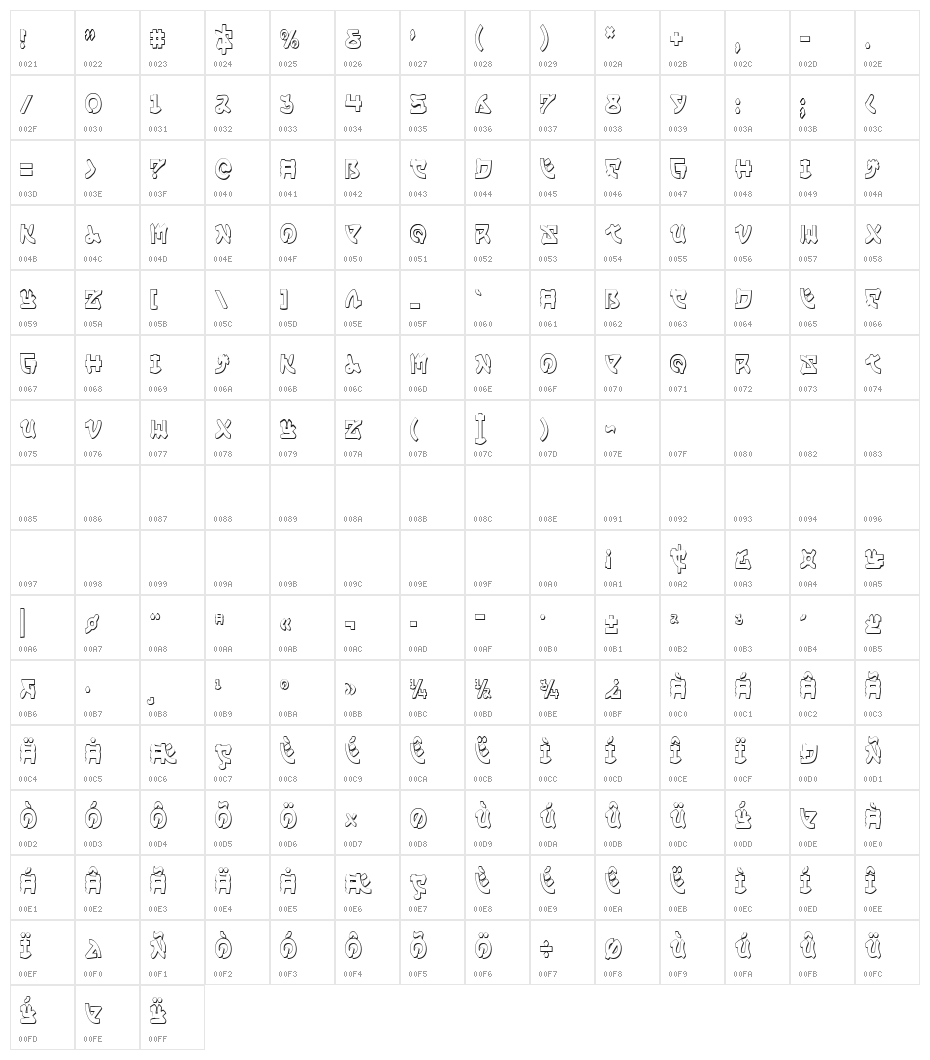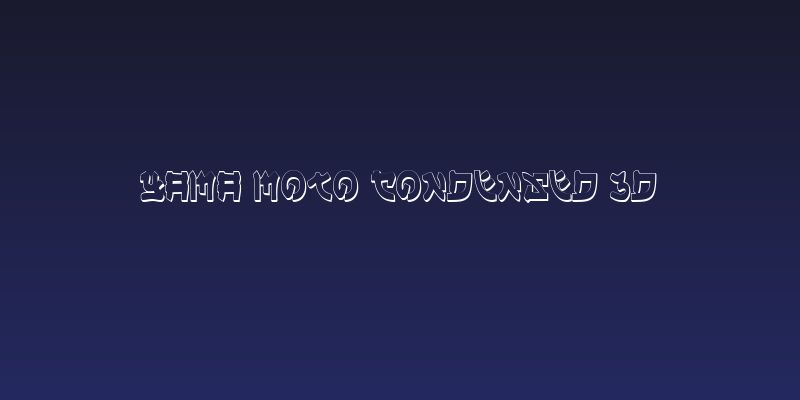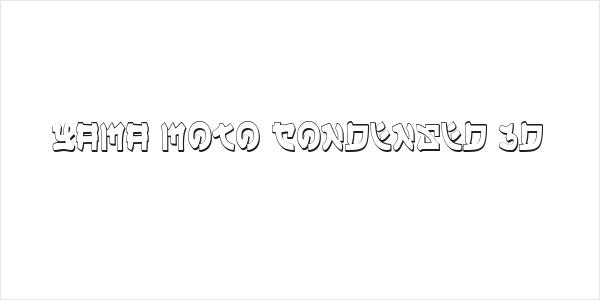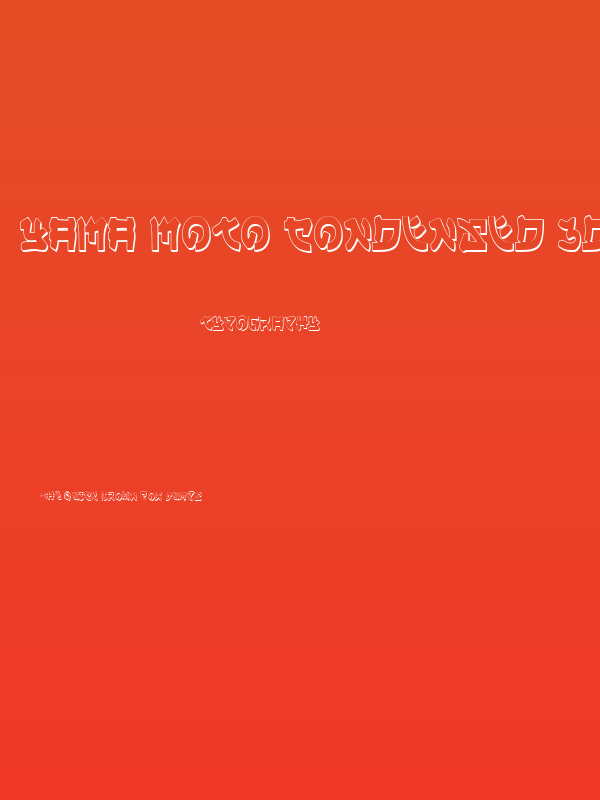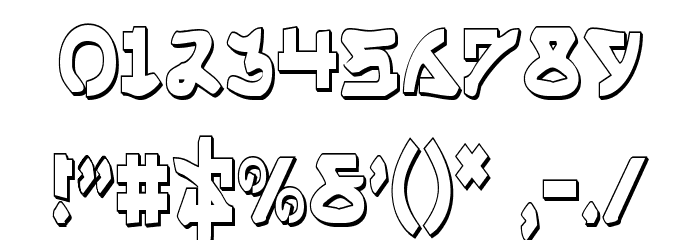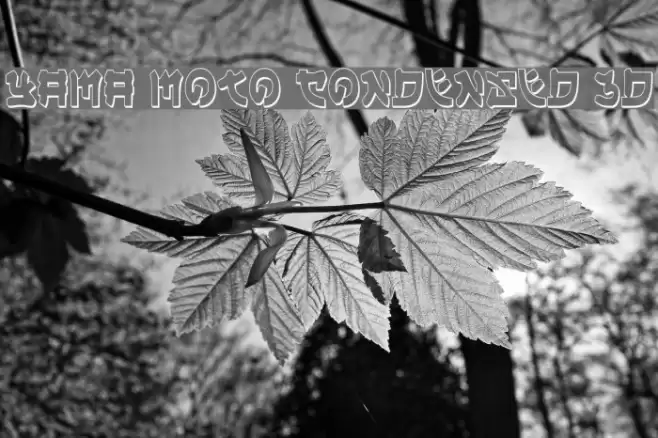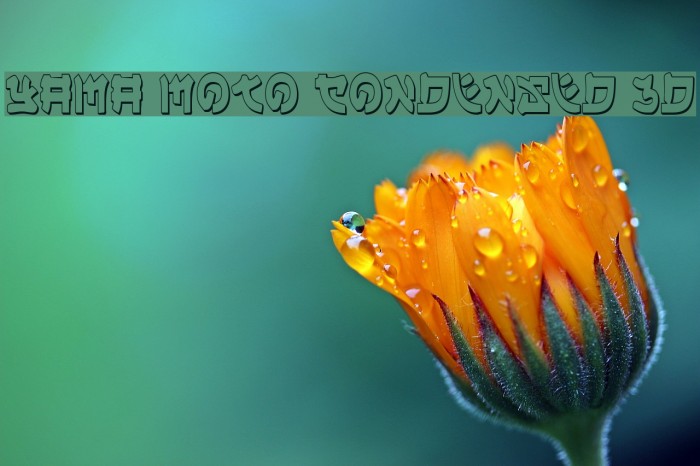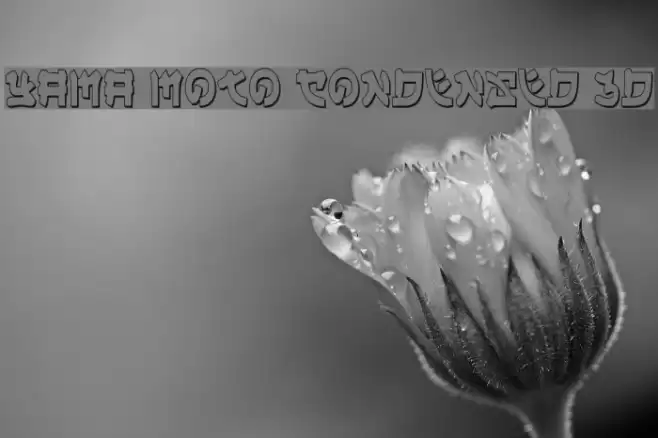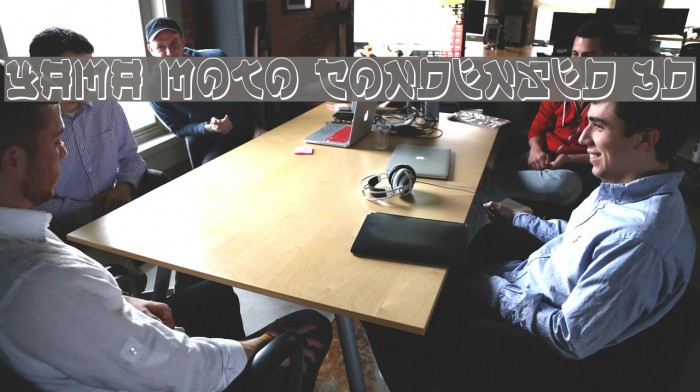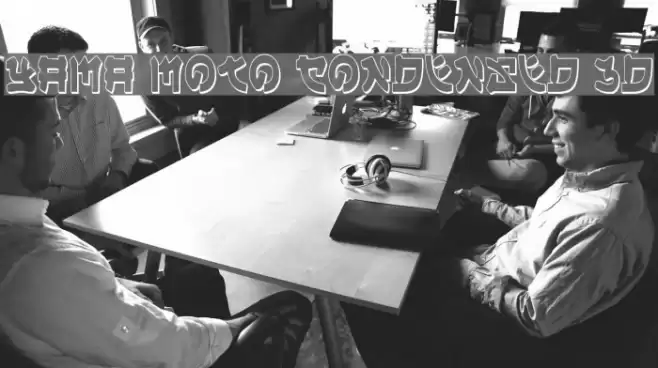
Yama Moto Condensed 3D Font
| Vorgeschlagene Projekte | Ideal for posters, video game titles, sci-fi themed projects, and branding that requires a modern, standout typeface. |